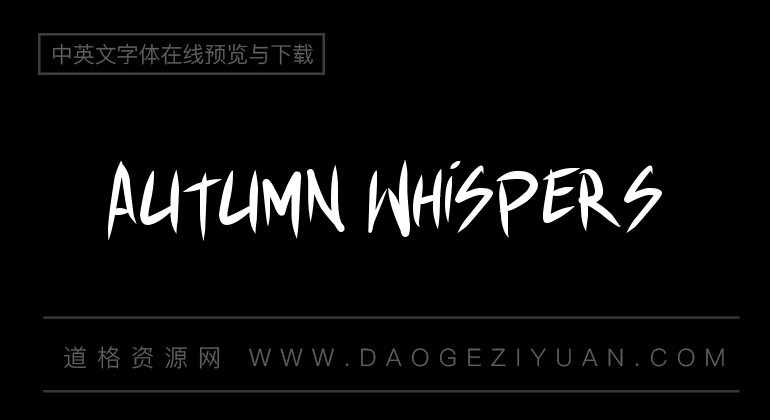
Autumn Whispers
Autumn Whispers 是一款设计师字体,它具有柔和、温暖的质感,具有明显的古典风格,拥有清新而优雅的特点,适用于各种文字排版。它具有良好的可读性,可以帮助你轻松地将你的文字转化为一个精美的设计作品。它适用于标题、标签、设计等多种应用场景,可以让你的设计更加精致、漂亮、精美。
Autumn Whispers是一款非常不错的手写艺术字体,具有很好的视觉感,适合于文化类的宣传设计、商业类品牌的广告和产品包装设计以及个性化文字排版等较多场景。